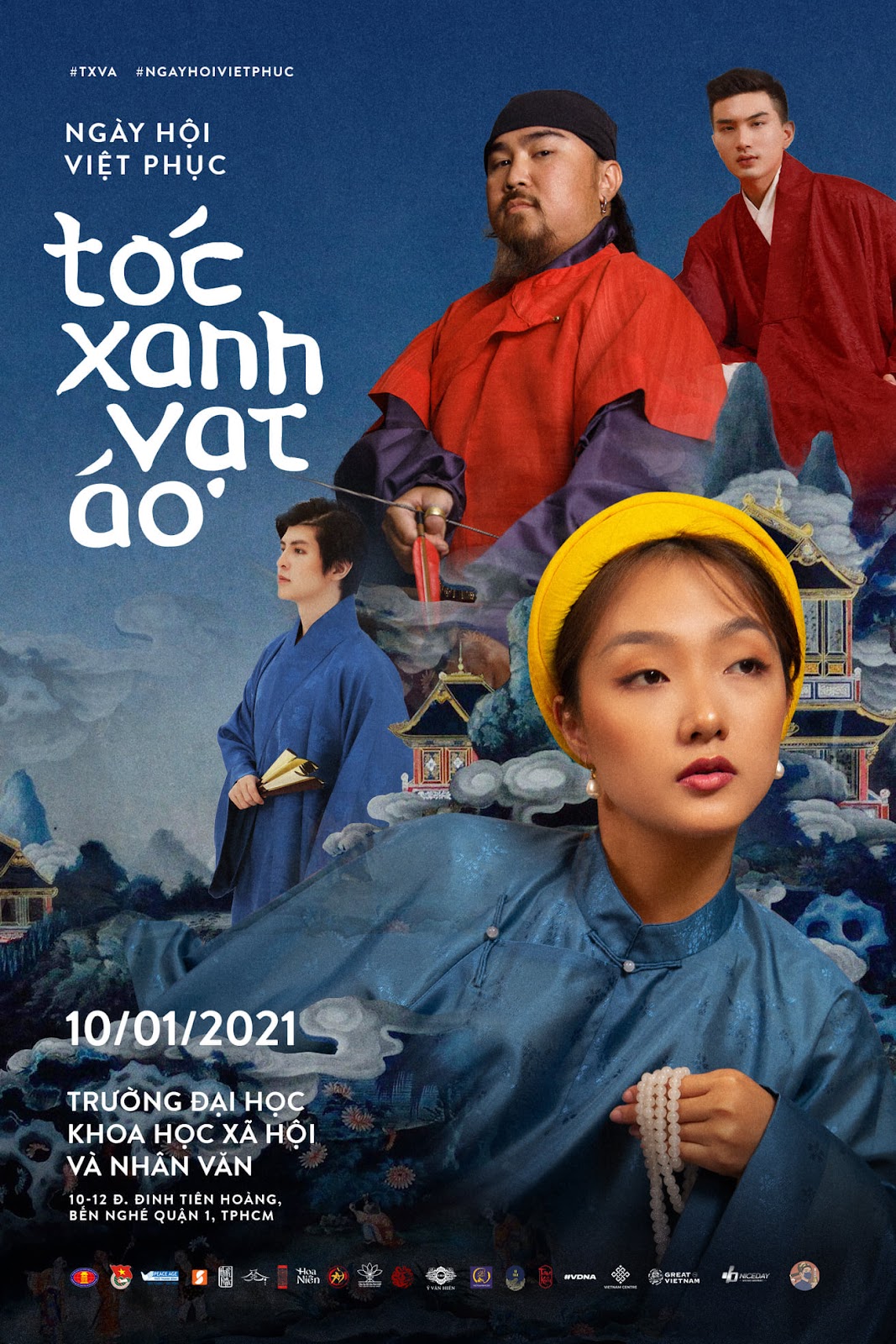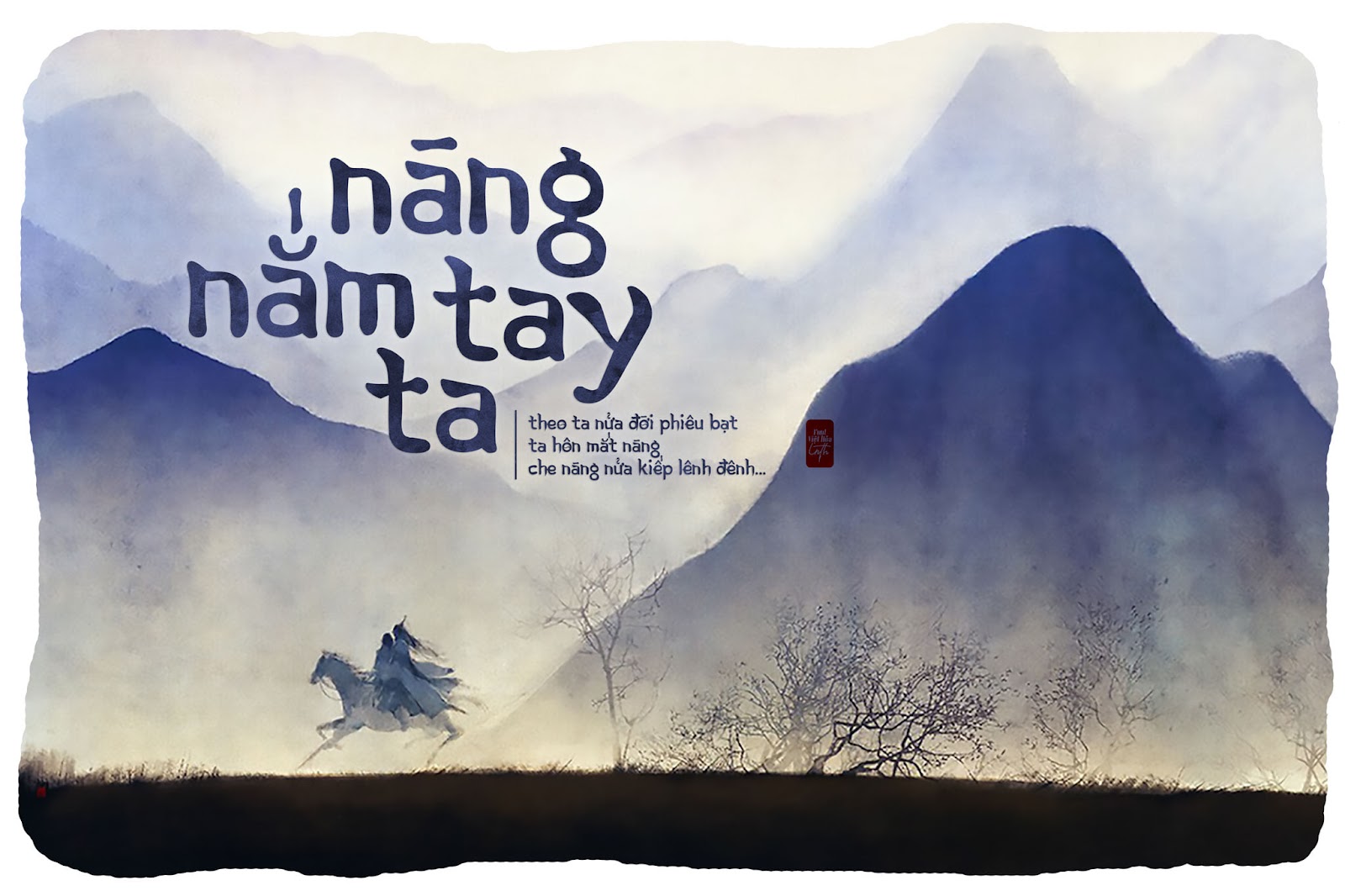
Font Korean Calligraphy Việt Hóa – Font thư pháp tuyệt đẹp
Font Korean Calligraphy Việt Hóa dựa trên bảng chữ cái Hàn Quốc được thiết kế bởi hiJoju, một font chữ dạng thư pháp cực đẹp với phong cách phương Đông phù hợp với các thiết kế cổ trang và nhiều thiết kế khác nhau.
Font Korean Calligraphy Việt Hóa